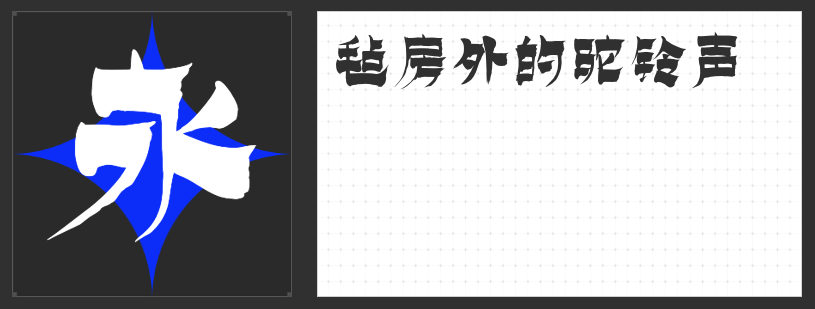
探索书法之美:精选书法字体推荐
在浩瀚的中华文化长河中,书法作为一门独特的艺术形式,以其千变万化的字体和深厚的文化底蕴,吸引着无数人的目光。今天,就让我们一起探索几种经典而富有魅力的书法字体,感受它们带来的视觉盛宴与心灵触动。
造字侠灵霄简繁 传神,字形饱满而富有张力,每一笔一划都透露设计师的深厚功底和独特风格。其运笔流畅自然,转折处圆润而不失力度,既保留了传统书法的韵味,又融入了现代设计的审美元素。无论是在阅读还是在设计中,这款字体都能带给人们一种独特的视觉享受和心灵触动。
作为字库书法字体的一员,造字侠灵霄简繁 传神不仅适用于各种正式场合的文档撰写,更是海报设计、品牌VI、广告创意等领域的理想选择。它以其独特的艺术魅力和广泛的应用价值,赢得了众多设计师和用户的青睐。如果你正在寻找一款能够彰显文化底蕴与个性的书法字体,那么造字侠灵霄简繁 传神绝对值得一试。
造字侠仗剑简繁 传神,每一笔都仿佛剑走偏锋,既有仗剑走天涯的洒脱不羁,又不失细腻传神的韵味。其简繁并用的设计,既保留了传统书法的古朴韵味,又符合现代审美的需求,让人一眼难忘。
无论是用于书籍封面、海报设计,还是品牌标识、广告文案,造字侠仗剑简繁 传神都能以其独特的风格和强大的表现力,为作品增添一抹不可复制的艺术魅力。它不仅是文字的载体,更是情感的传递者,让每一个字都充满了生命力和感染力。
在追寻书法之美的道路上,我们遇到了造字侠磅礴简繁这款令人瞩目的字库书法字体。它以其独特的磅礴气势和简繁并蓄的巧妙融合,成为了设计领域的新宠。
造字侠磅礴简繁,每一笔一划都蕴含着力量与美感,仿佛是大自然中壮丽山川的缩影,展现出无尽的雄浑与辽阔。造字侠磅礴简繁不仅保留了传统书法的韵味,更赋予了字体现代感和时尚气息,让人在欣赏之余,也能感受到一种跨越时空的文化传承。
造字侠永刚漆书简繁,其独特之处在于其漆书的质感与风格。漆书,以其厚重的笔触和独特的墨色效果,自古以来便备受推崇。
在设计中运用造字侠永刚漆书简繁,不仅能够赋予作品独特的艺术气息,还能展现出设计者的深厚文化底蕴与独特审美眼光。无论是品牌标识、海报设计,还是书籍装帧、广告宣传,这款字体都能以其独特的魅力和强烈的视觉冲击力,为作品增色添彩,留下深刻印象。
总之,书法字体是传统书法与现代技术的完美融合,是传承与创新的艺术瑰宝。它们不仅丰富了我们的设计语言,也让我们在数字化时代依然能够感受到传统文化的魅力与韵味。在未来的日子里,相信书法字体将会继续发光发热,为设计领域带来更多惊喜与可能。